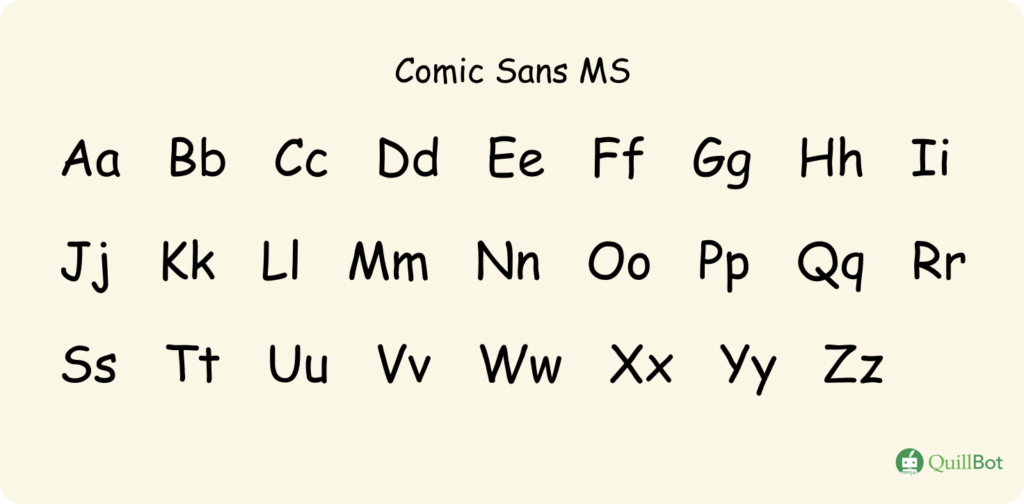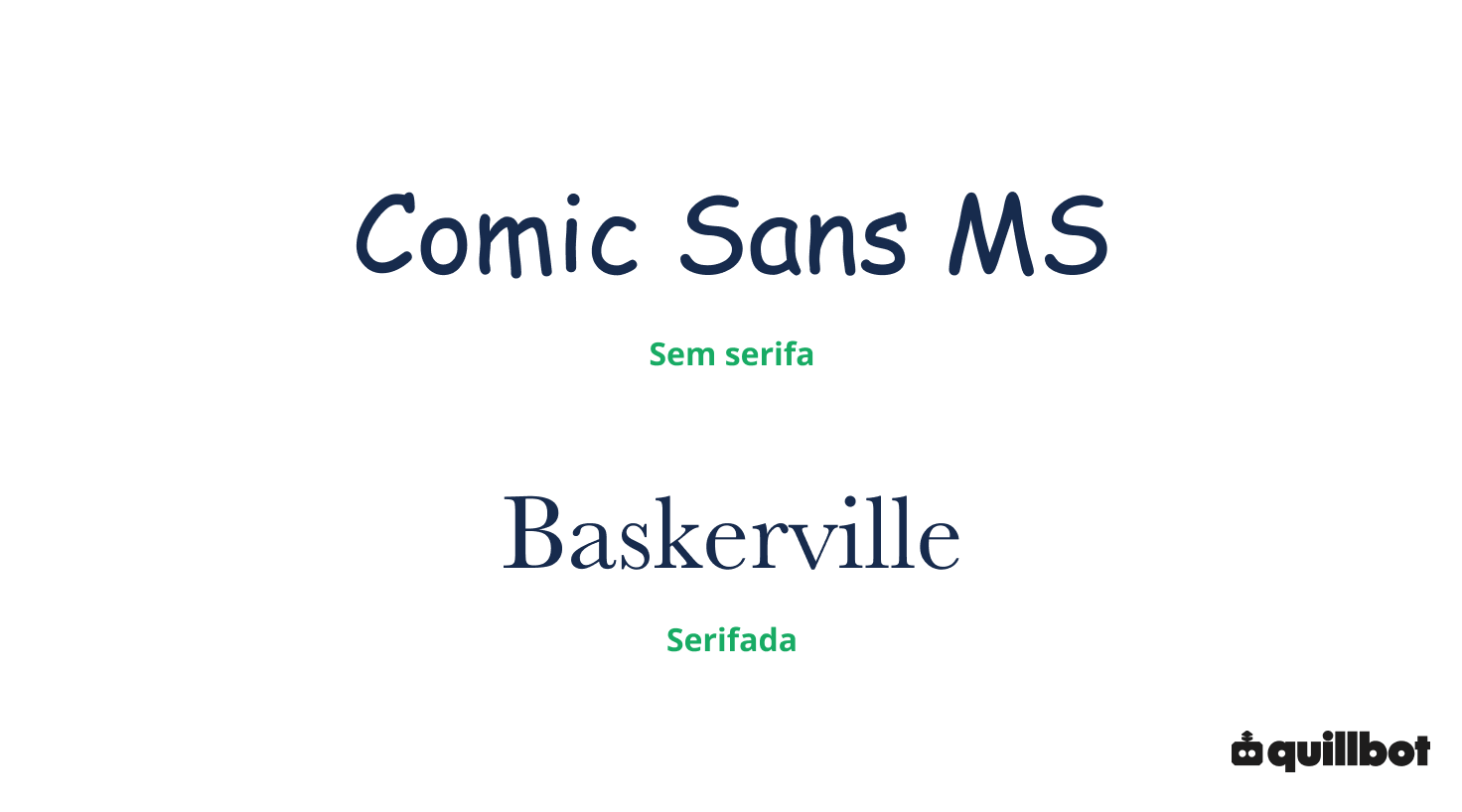
Comic Sans | Usos e história
Ou você ama ou odeia; muitas vezes, ambos ao mesmo tempo, mas uma coisa é certa: a Comic Sans MS é uma fonte que não deixa ninguém indiferente.
E, por bons motivos… não se trata de uma tipografia como qualquer outra, mas sim de um verdadeiro fenômeno cultural que marcou a cultura pop das décadas de 2000 e 2010.
- Ano de criação: 1995
- País de origem: Estados Unidos
- Criador: Vincent Connare (para a Microsoft)
- Tipo de fonte/Classificação VoxAtypi: manual
- Tipo de serifa: sem serifa
- Popularidade: + (muito difundido e popular em determinado momento, mas agora tem reputação de ultrapassada e pouco profissional)
- Imagem transmitida: informal, lúdica, descontraída, “cartunesca”, ou até mesmo amadora e antiquada.
- Destaque especial: facilita a leitura para pessoas com dislexia.
Como qualquer tendência social, a Comic Sans MS, naturalmente, tem seus inimigos, entre eles os defensores do “mau gosto tipográfico”.
Mas, lembre-se… é verdade que a Comic Sans MS não é desenhada com os traços mais finos e dificilmente seria vista na capa de uma tese acadêmica, mas continua sendo um símbolo evocativo de um espírito divertido e de uma era ultracriativa.
Quanto ao uso atual, ainda é possível utilizá-la, mas é aconselhável cautela.
Fonte Comic Sans MS: história e desenvolvimento
A Comic Sans MS pode ser considerada uma fonte “cartunesca” ou infantil, já que esse era o objetivo original.
Em 1994, Vincent Connare, tipógrafo da Microsoft Corporation, recebeu a missão de desenvolver a tipografia de um novo software, o Microsoft Bob.
O Microsoft Bob foi um fracasso monumental, com o abandono do projeto antes mesmo do lançamento do Windows 98.
As crianças estavam entre os usuários-alvo de Bob. Por isso, a fonte Comic Sans MS foi criada para dar um aspecto lúdico à interface do software, cuja estética lembrava os desenhos animados da época.
Na verdade, o nome Comics, que significa “quadrinhos” em português, é bastante transparente quanto às suas intenções.
Integrada por padrão no Windows, a Comic Sans MS agrada ao público em geral por seu aspecto informal.
É encontrada em muitos lugares, inclusive fora da web, como em cartazes escolares, anúncios, placas de rua, apresentações em PowerPoint e sites dos anos 2000. Sua disponibilidade quase universal e seus traços descontraídos tornam a Comic Sans a escolha padrão de milhões de usuários não profissionais, principalmente os jovens.
É precisamente a sua onipresença, aliada a usos que são considerados fúteis e já ultrapassados, que consolida a sua má reputação, apesar de ganhar um charme ligeiramente vintage.
Atualmente, a Comic Sans MS funciona como uma referência ao passado das primeiras redes sociais, despertando uma certa nostalgia.
É por isso que ainda encontramos essa fonte em um número significativo de memes ou em posts daqueles que pretendem ser levemente bregas.
Características da Comic Sans MS
Apesar de seu estilo peculiar e criativo, a Comic Sans MS é uma fonte do tipo sem serifa, ou sans serif.
Suas características também se refletem em seu nome, já que Sans significa “Sem” e MS significa “Microsoft”.
Comic Sans MS é uma fonte sem serifa, também chamada de fonte sans-serif. Esse tipo de letra é o oposto das fontes com serifa.
- As fontes serifadas possuem pequenos “pés”, ganchos ou traços decorativos nas extremidades dos caracteres. Elas evocam um design clássico e sério, conferindo à comunicação um caráter simbólico e institucional, transmitindo certa autoridade. Também são amplamente utilizadas em editoras e mídias impressas, pois são consideradas mais confortáveis para a leitura de textos longos. Exemplos de fontes serifadas incluem: Baskerville, Garamond, Times New Roman e Palatino Linotype.
- As fontes sem serifa não possuem serifas. Suas linhas são retas e limpas e sua aparência é moderna e minimalista; com design limpo, porém acessível. Elas são frequentemente usadas na web devido à sua legibilidade otimizada para telas e à sua aparência impactante. Exemplos de fontes sem serifa: Arial, Calibri, Futura, Open Sans, Roboto e Tahoma.
Usos da Comic Sans MS
Se a Comic Sans MS se tornou tão popular em tempo recorde, foi principalmente porque se destacou de outras fontes icônicas do gênero, como Times New Roman ou Arial.
Não é, portanto, surpreendente que os anunciantes o tenham usado amplamente durante algum tempo, apesar da sua falta de praticidade do ponto de vista puramente gráfico.
O espaçamento inadequado entre os caracteres, a espessura desarmoniosa e o tratamento desastroso das curvas são deficiências que não serão imediatamente aparentes para os usuários comuns, mas representam um desafio significativo para os designers gráficos que desejam utilizá-la.
Atualmente, tipografia refere-se à arte ou técnica de organizar textos e letras de maneira clara e agradável.
- Qual é a diferença entre tipografia e fonte?
-
Tipografia é o conceito geral de escolhas visuais envolvendo letras e textos.
Fonte é um tipo específico de letra, em geral, um arquivo digital.